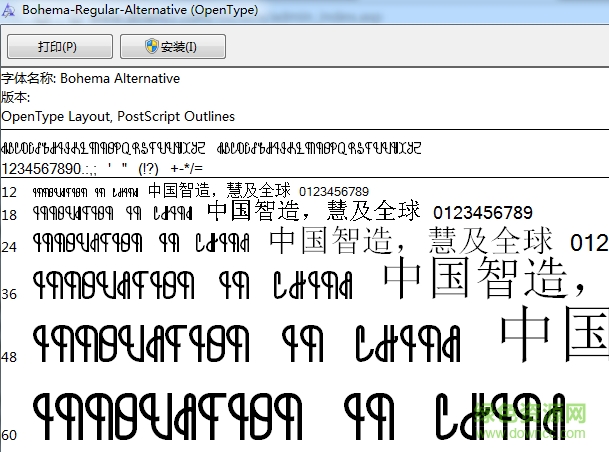
Bohema英文字體
Bohema字體是一款超好用的英文字體,這款字體由圖形設(shè)計(jì)師及插畫(huà)家 Joao Oliveira 創(chuàng)作而成,藝術(shù)裝飾風(fēng)格中帶著摩登氣息。非常適合復(fù)古的設(shè)計(jì),或是文字標(biāo)題,品牌推廣,產(chǎn)品促銷(xiāo)或是其他設(shè)計(jì)場(chǎng)合。有喜歡這款字體的朋友就趕快來(lái)綠色資源網(wǎng)下載使用吧!
Bohema字體
Bohema字體是一款英文字體,該字體擁有十分全面的設(shè)計(jì)模板,讓用戶(hù)能夠享受更全面的個(gè)性字體,有需要的朋友就趕快來(lái)綠色資源網(wǎng)下載吧!